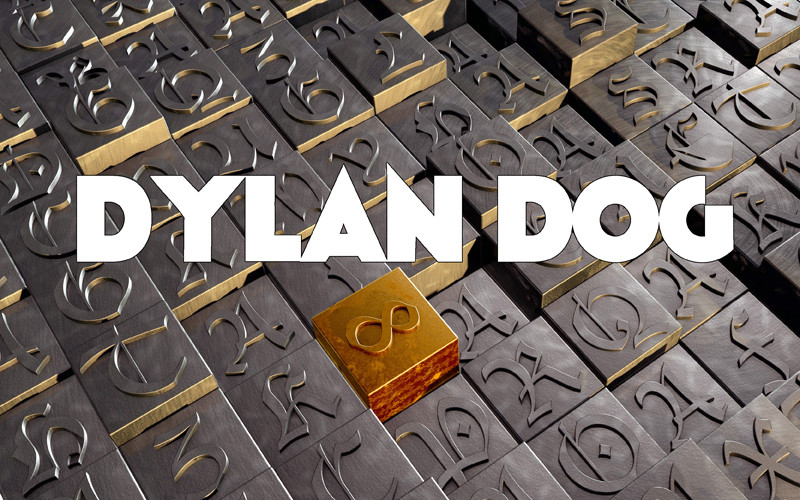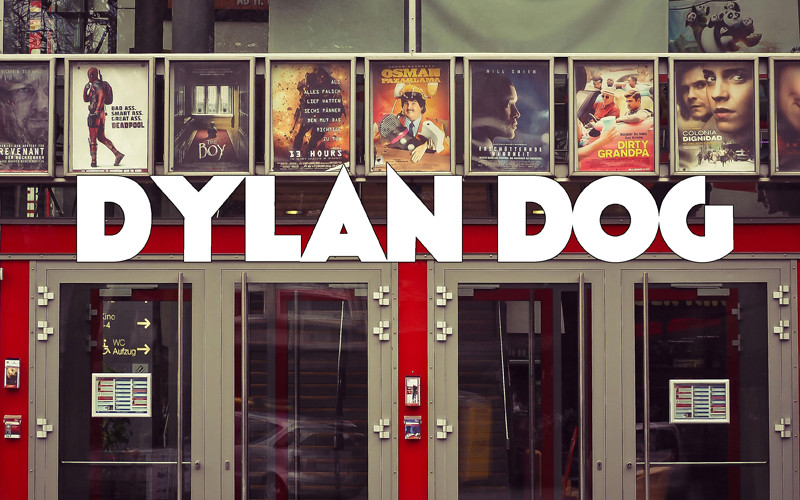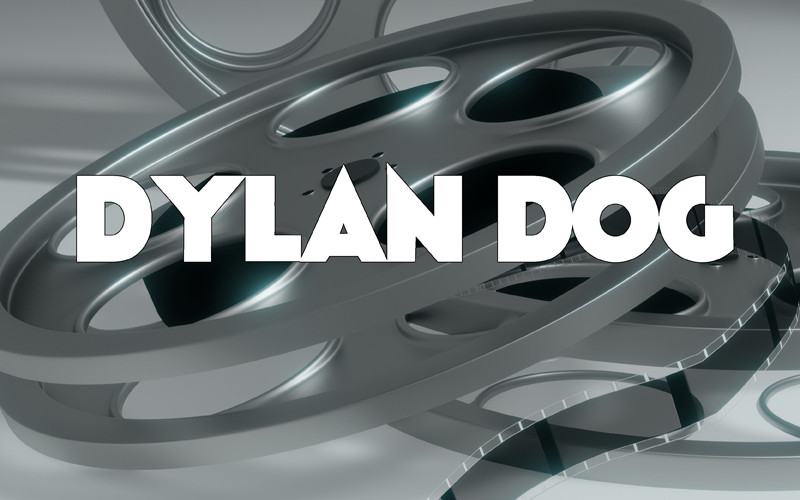
Direttamente dal film diretto da KEVIN MUNROE e interpretato da BRANDON ROUTH, il font inedito per tutti gli estimatori del film.
Directly from the film directed by KEVIN MUNROE and starring BRANDON ROUTH, the new font for all fans of the film.
Direttamente dal film diretto da KEVIN MUNROE e interpretato da BRANDON ROUTH, il font inedito per tutti gli estimatori del film.
Directly from the film directed by KEVIN MUNROE and starring BRANDON ROUTH, the new font for all fans of the film.